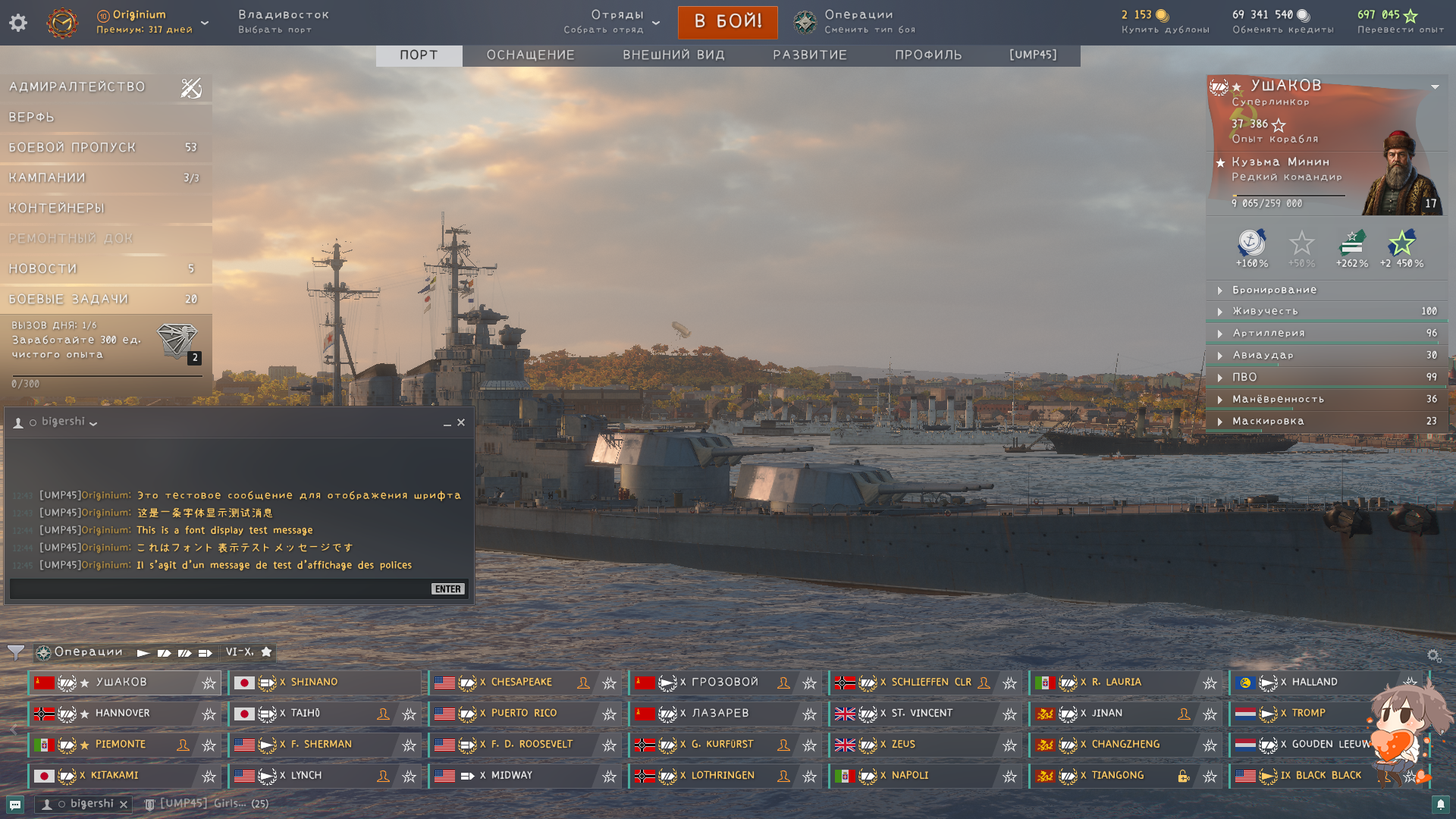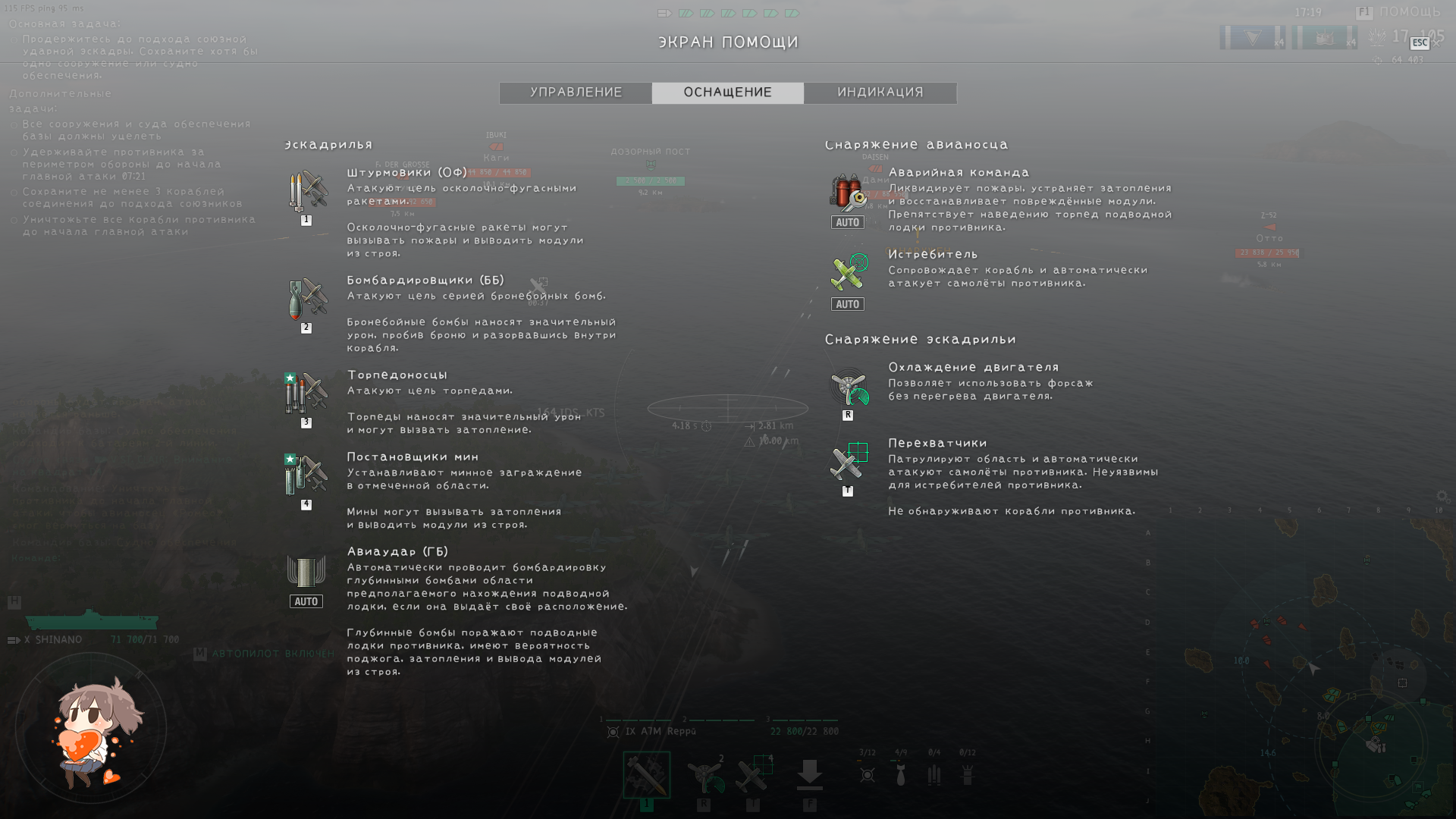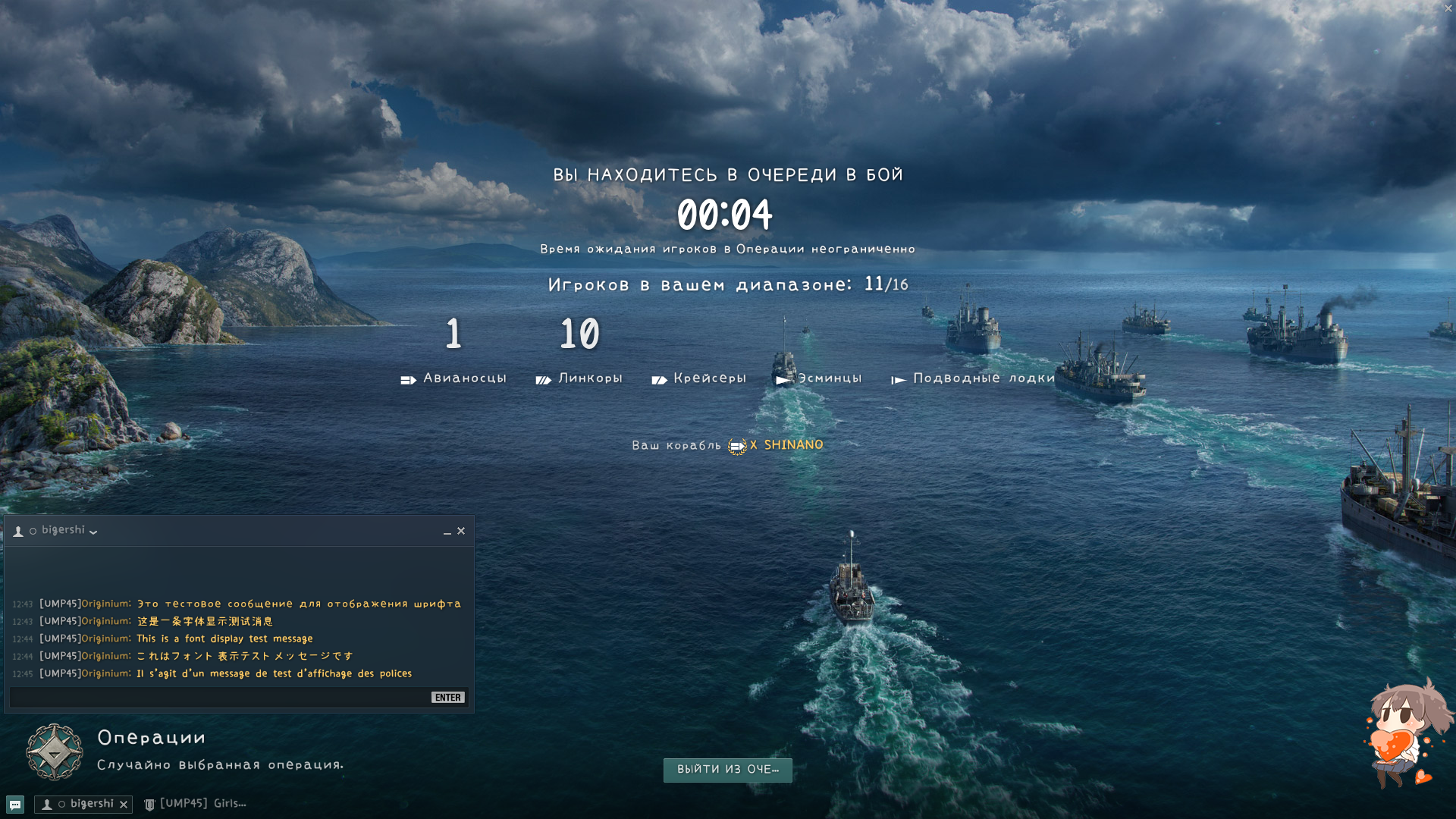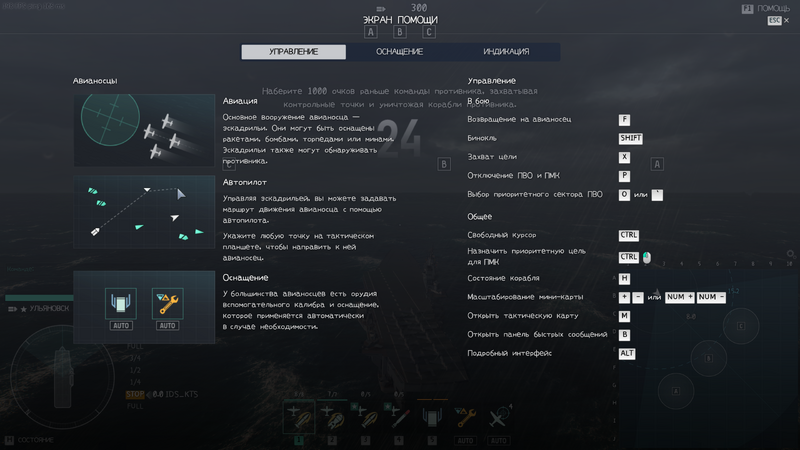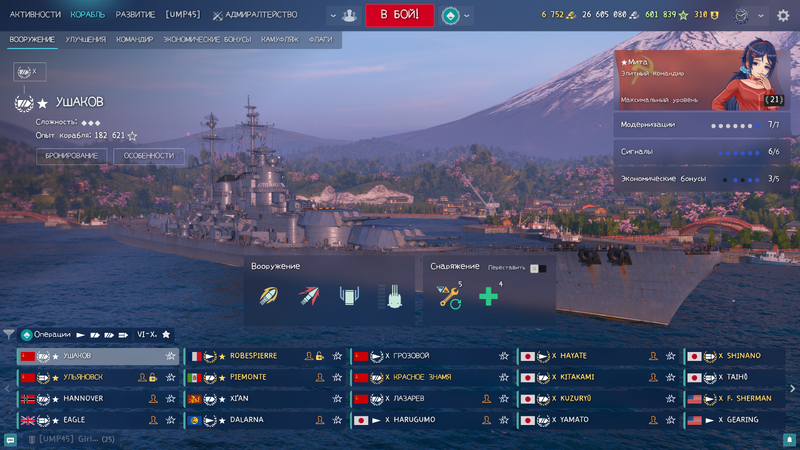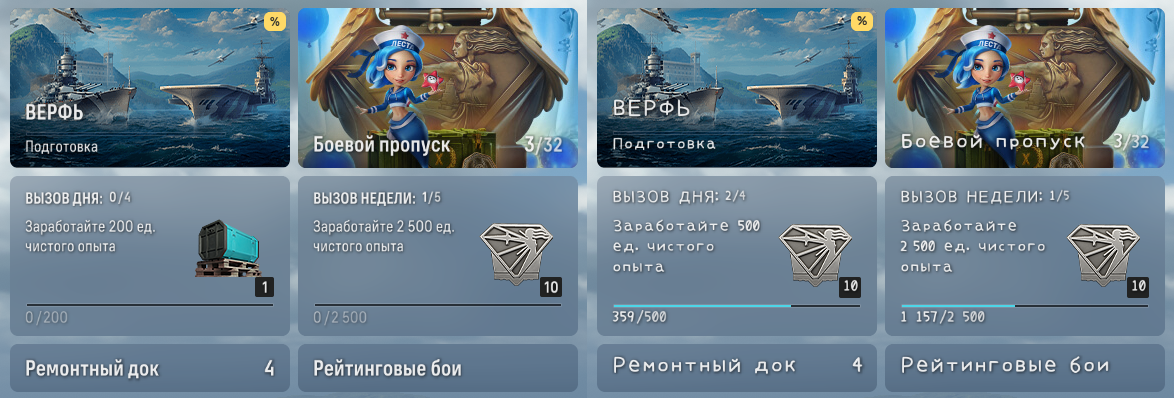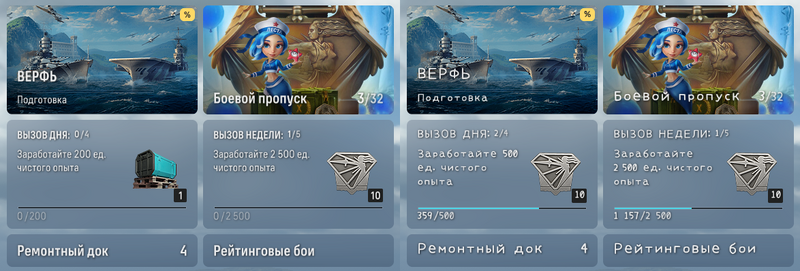
[All] Шрифт Мита
Описание:
Этот шрифт происходит от китайского шрифта игры "Мита", симпатичный и поддерживает практически все языки (русский, китайский, английский, японский, французский, немецкий и т.д.)
• Расстояние между символами и числами было уменьшено на 20%, чтобы соответствовать пользовательскому интерфейсу Мир кораблей
Актуально в связи с изменениями интерфейса. Стало намного комфортнее по сравнению с Вагоном Артемия Лебедева.
Только вот немного съезжает окошко снаряжения, если там не больше 3-х модулей.
P.S. В разделе Клан и Адмиралтейство шрифт остался прежним.
Адмиралтейство и Клан — это веб-интерфейсы, шрифтовые модули нельзя изменить.:fish_aqua:
Кроме того, я изменил форму и интервал шрифта, чтобы он больше соответствовал вашим требованиям.